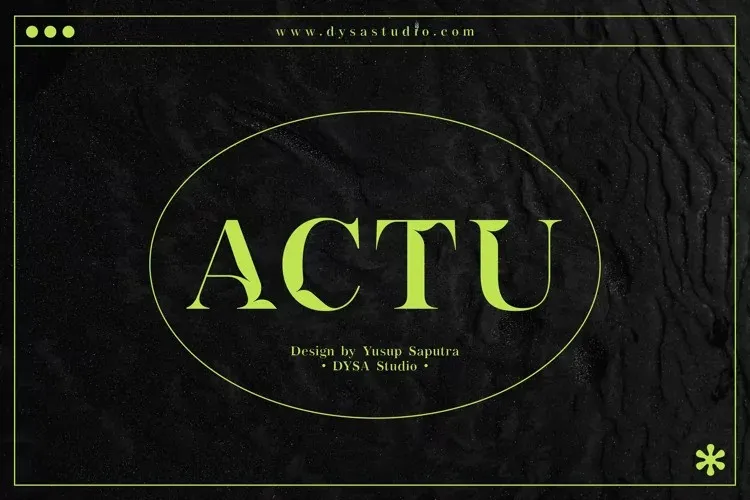
A fonte Actu é uma nova tipografia para exibição inspirada no estilo brutalismo, criada pela DYSA Studio. Seus traços retos e robustos combinam com um design clean, moderno e minimalista, oferecendo grande versatilidade para projetos gráficos ou editoriais. Ideal tanto para designers buscando estilos de elegância minimalistas quanto para pessoas que buscam formas contemporâneas e limpas em seus trabalhos, a fonte Actu se adapta perfeitamente para uma variedade de aplicações como logotipos, materiais de marca, cartões de visita, cupons de presente, camisetas, capas, miniaturas, impressão, posters, fotografia e até mesmo frases. Seja você um designer gráfico ou um criador de conteúdo que procura uma fonte para sua próxima produção, a fonte Actu certamente se adequará às suas necessidades.